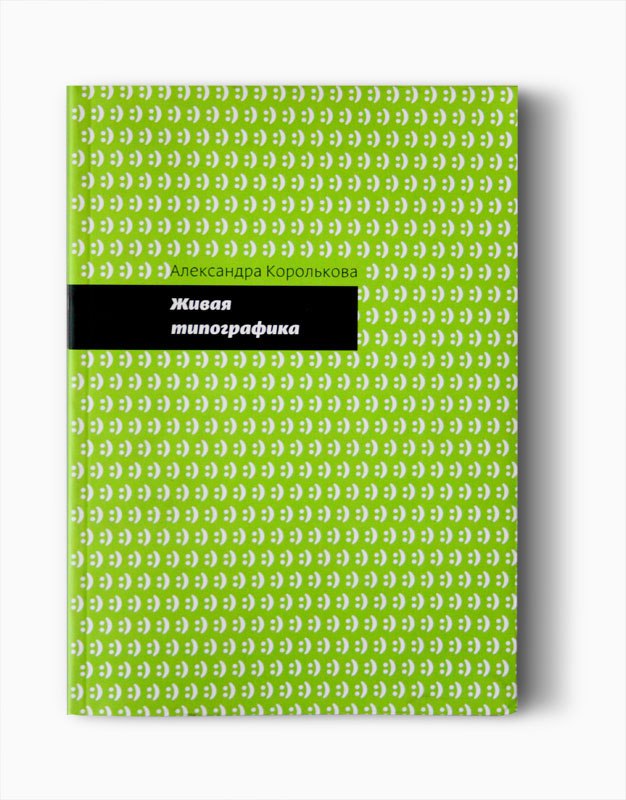
“Живая типографика”, Александра Королькова
В книге живым и доступным языком изложены основные правила и закономерности типографики — «искусства расположения наборного материала на плоскости листа». Рассмотрены история и различные классификации наборных шрифтов и основные принципы их подбора и применения, способы размещения материала на развороте, принципы и правила набора. Книга предназначена для студентов высших учебных заведений, изучающих графический и книжный дизайн. Кроме того, она будет полезна практикующим дизайнерам (в том числе, дизайнерам книги и начинающим дизайнерам наборного шрифта).